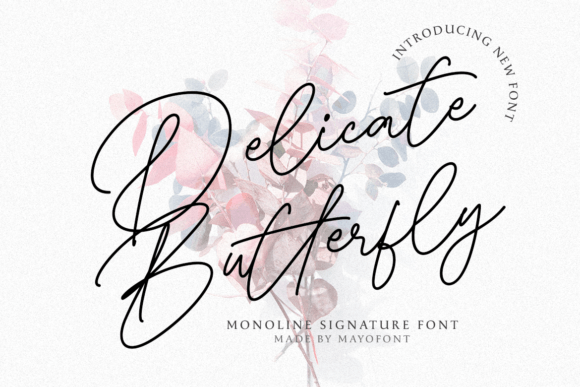
Delicate Butterfly
Jika anda sedang mencari aset berkualiti tinggi seperti Delicate Butterfly, pakej premium ini merupakan pilihan yang hebat untuk projek kreatif anda.
Dicipta dengan ketepatan, Delicate Butterfly menyediakan vektor yang bersih, tipografi yang licin dan lesen komersial untuk ketenangan fikiran.
Sama ada anda mencipta produk POD (Print on Demand), jemputan perkahwinan atau grafik media sosial, Delicate Butterfly amat bersesuaian.